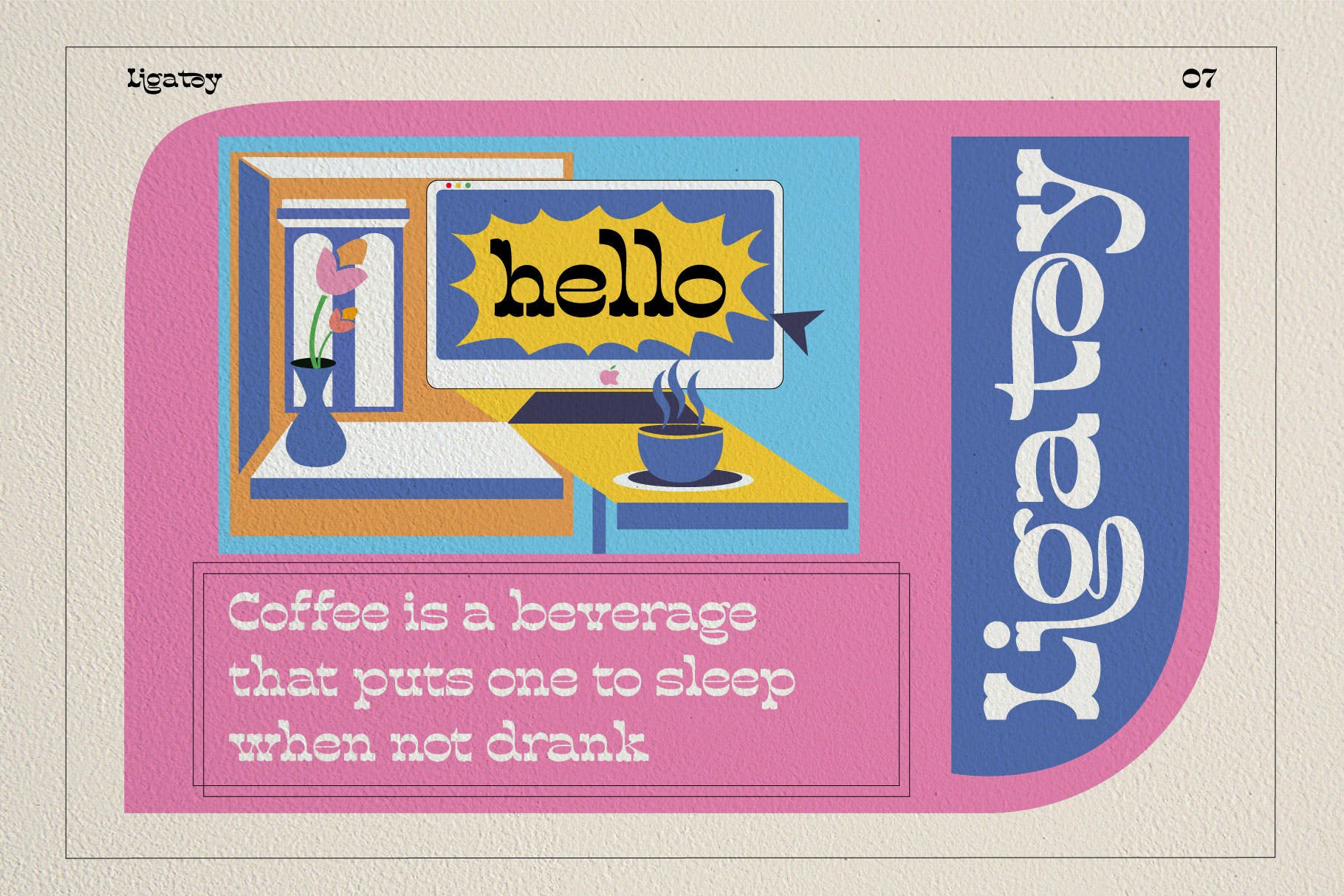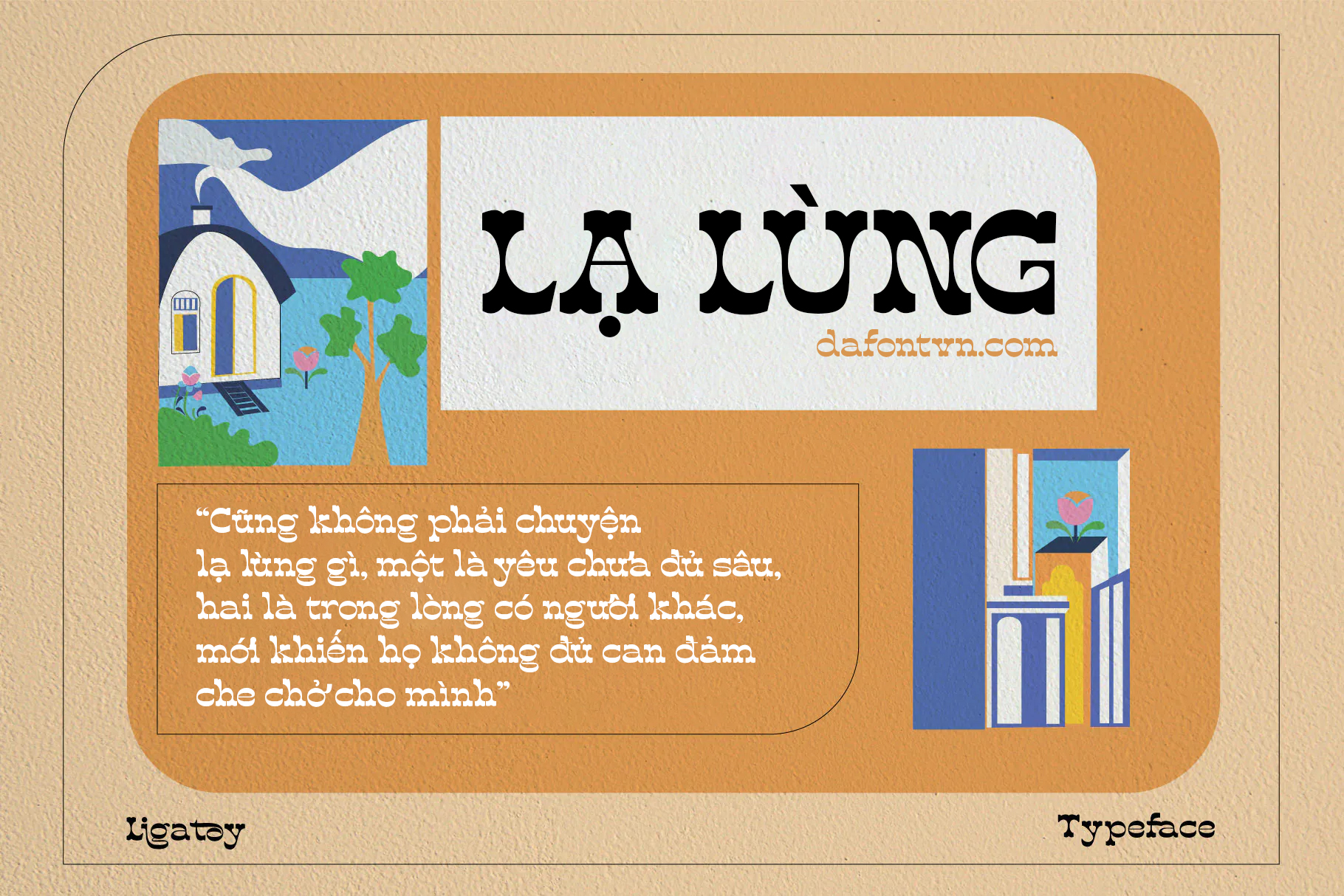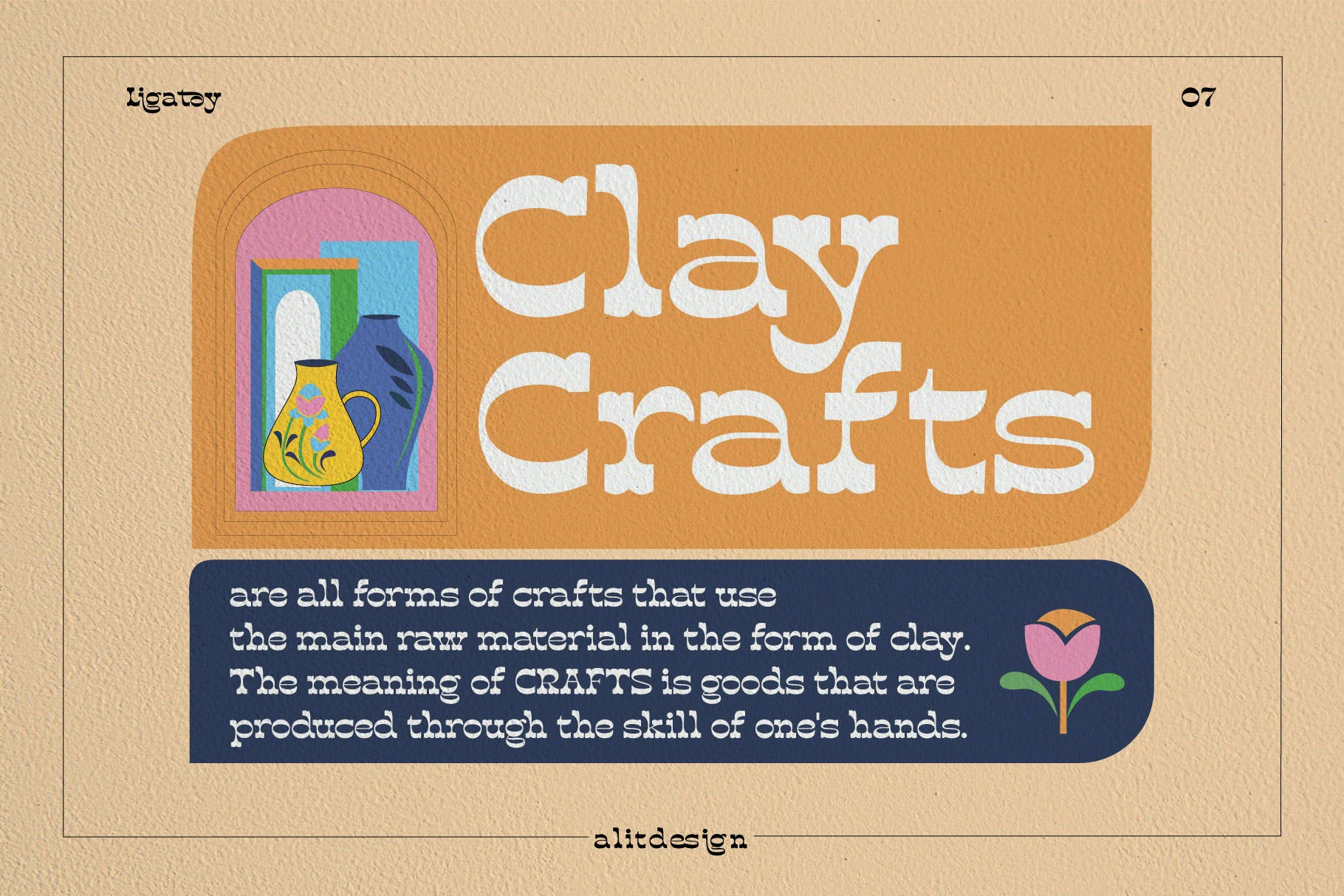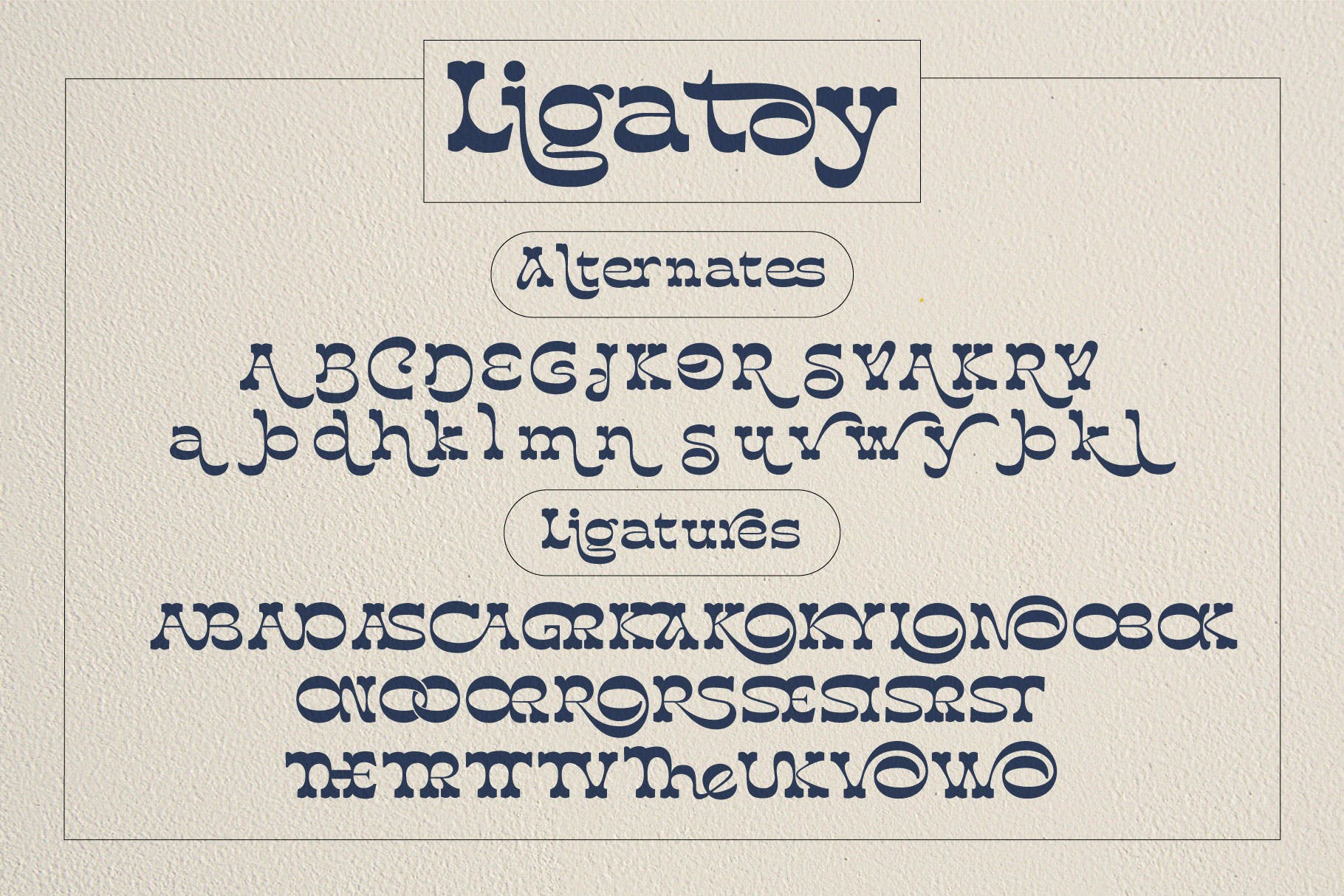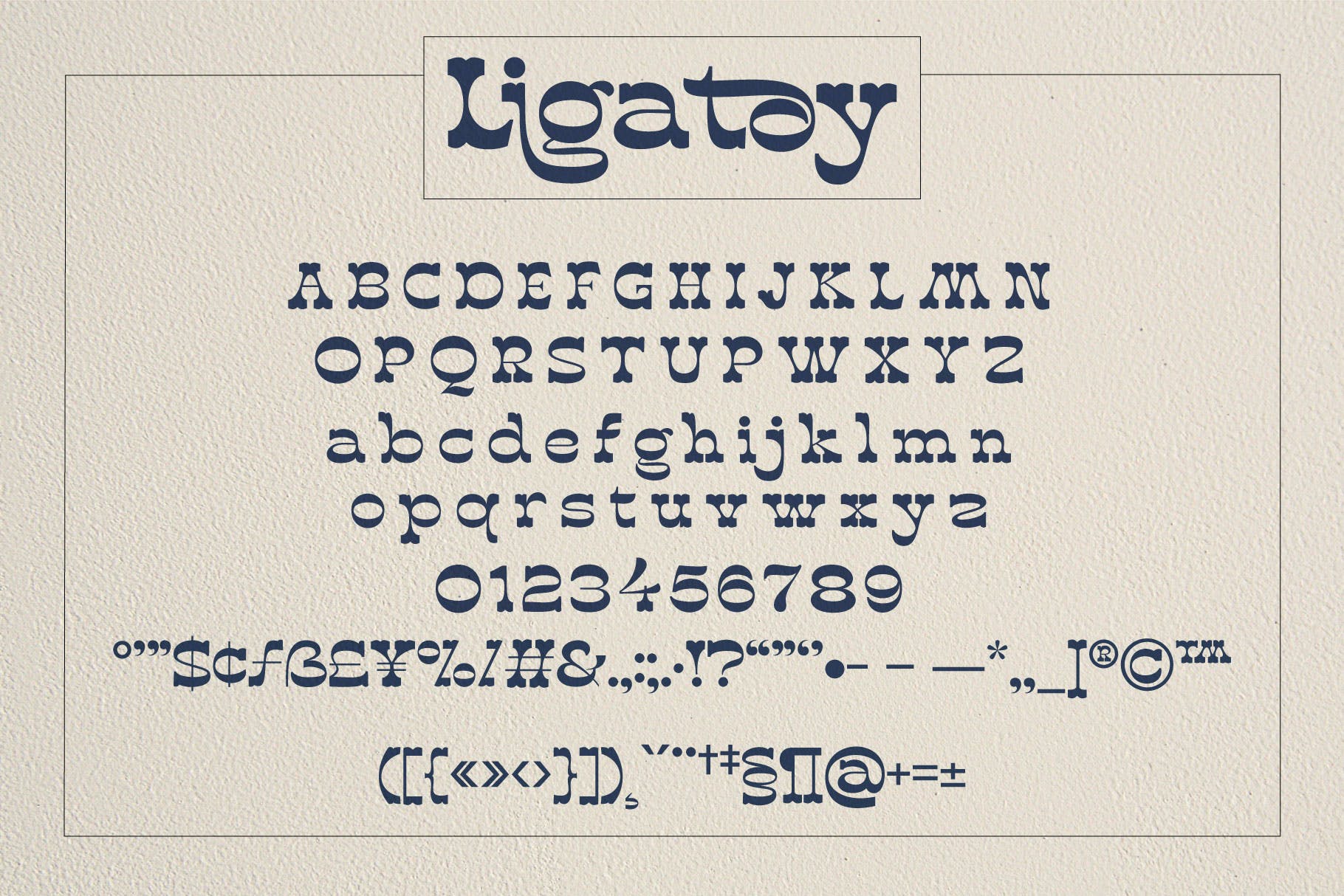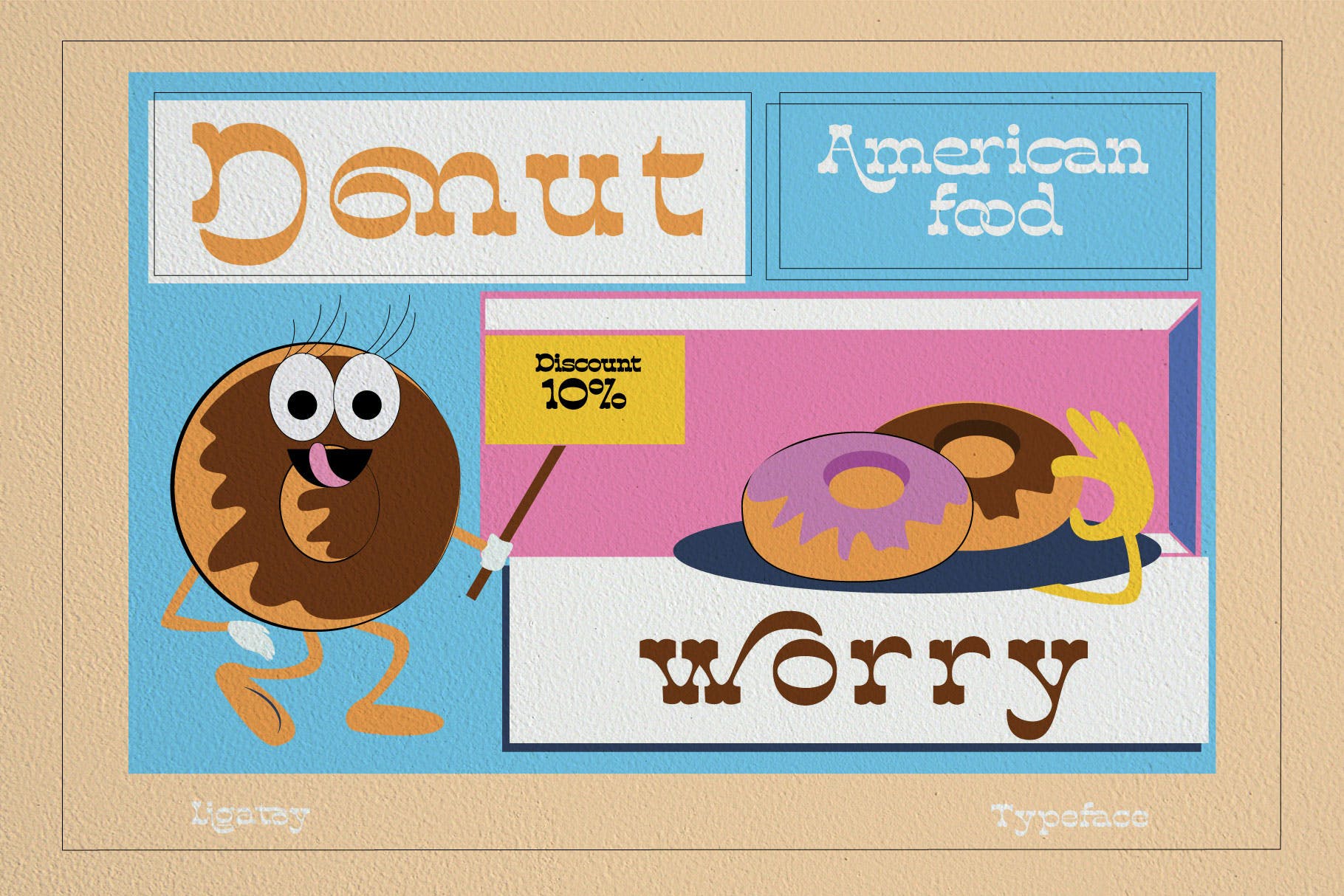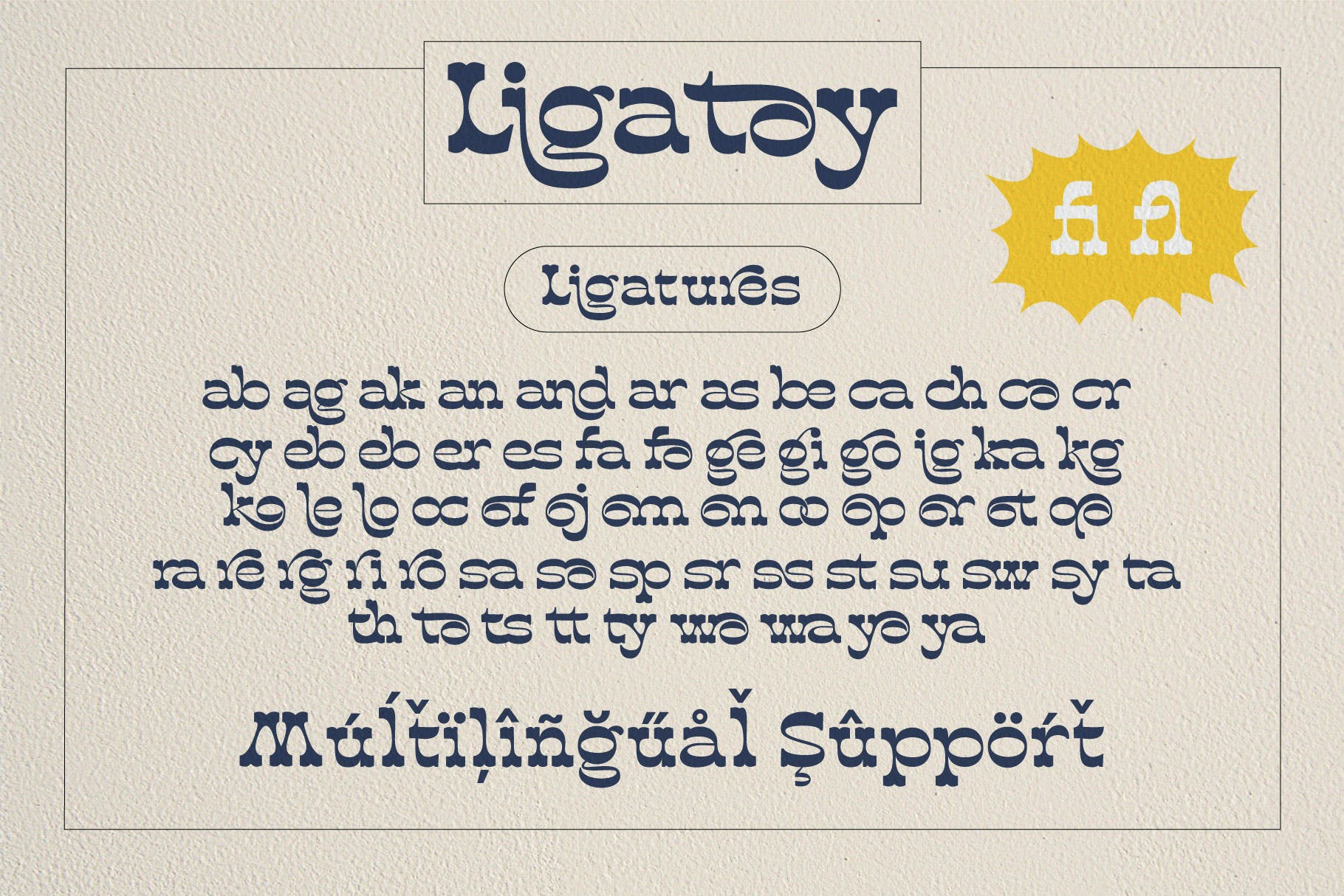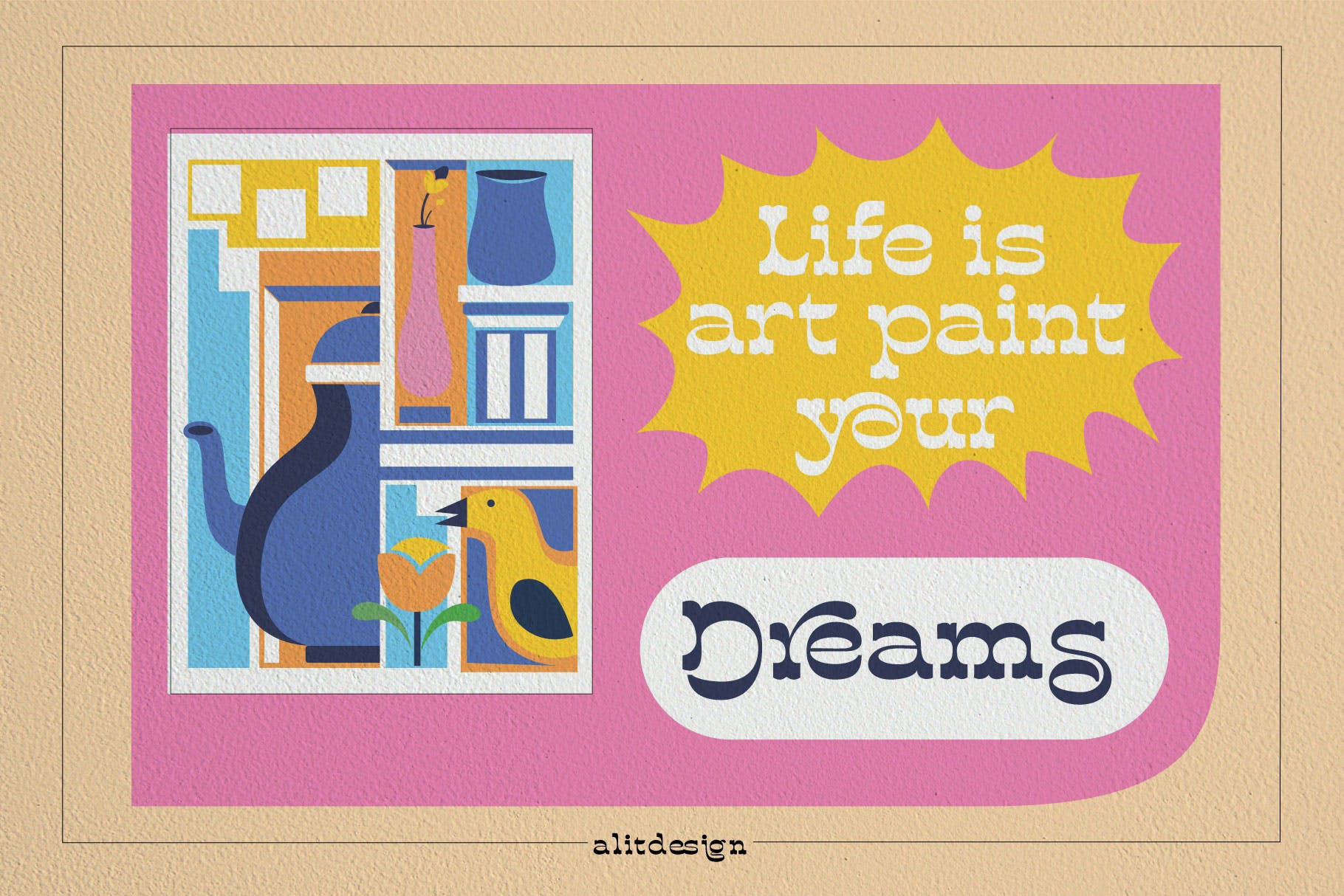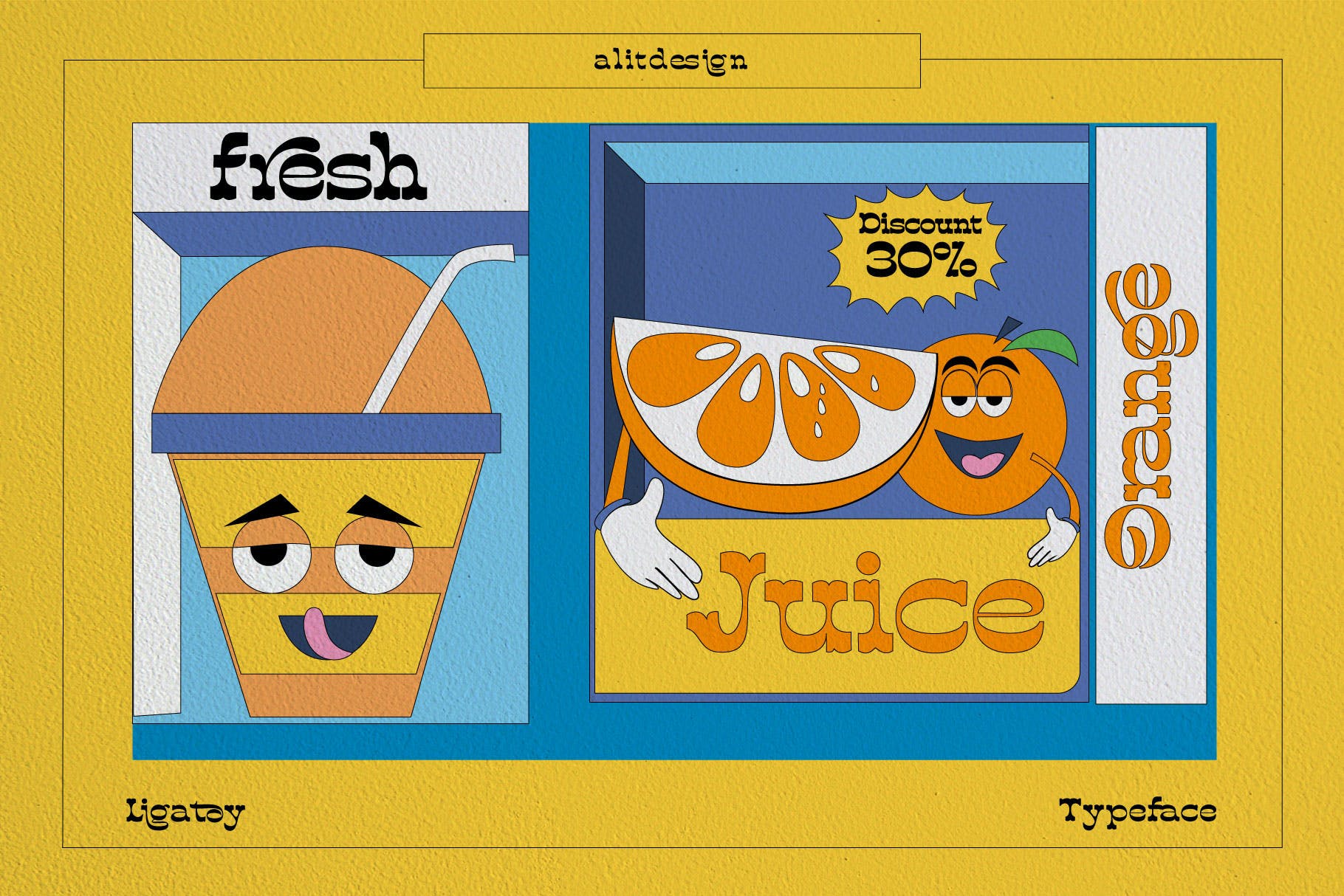
[Serif] Ligatoy Font – Font đẹp hỗ trợ Tiếng Việt
Giới thiệu Font Ligatoy Typeface. Font chữ này được lấy cảm hứng từ phong cách thiết kế của những năm 70. Phong cách hài hước, vui nhộn, cổ điển, có giá trị thẩm mỹ và độc đáo, bên cạnh đó font chữ Ligatoy rất dễ nhớ và trở thành hình ảnh của một thiết kế tuyệt vời.
Ligatoy Typeface rất tốt để trở thành bộ sưu tập font chữ của bạn vì font chữ này rất độc đáo và dễ áp dụng cho bất kỳ phương tiện truyền thông nào có ý tưởng thiết kế không quá nghiêm túc, lôi cuốn, cổ điển, hài hước và độc đáo.
Đặc trưng:
• Bộ ký tự AZ
• Chữ số và Dấu câu (Chuẩn OpenType)
• Thay thế phong cách
• Đa ngôn ngữ
Ligatoy Font
Font hỗ trợ Tiếng Việt luôn rồi nhé các bạn
Font Ligatoy Việt hóa